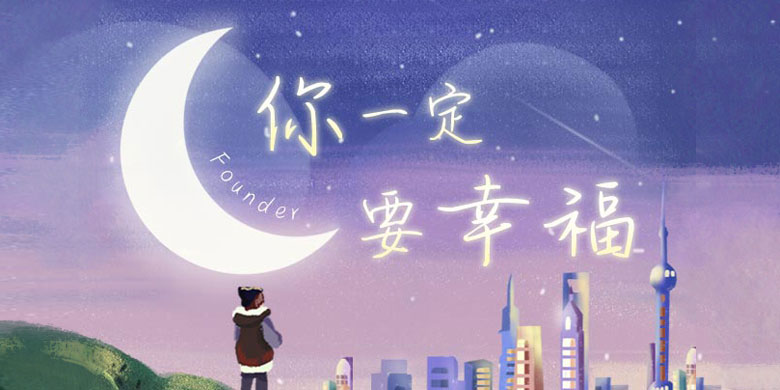
方正手迹-你一定要幸福
品牌:方正手迹设计师:余丹发行时间:2020字库编码:大陆简体(GB2312-80)分类:常规书写·硬笔字体属性:精品字
这款字连笔较少,中宫宽松,一笔一画凸显真心,如同手写的情书,告诉你一定要幸福。作为正文排版,阅读极具舒适度。适用于现代诗歌、短文的排版以及文化、商业类品牌的广告语设计。